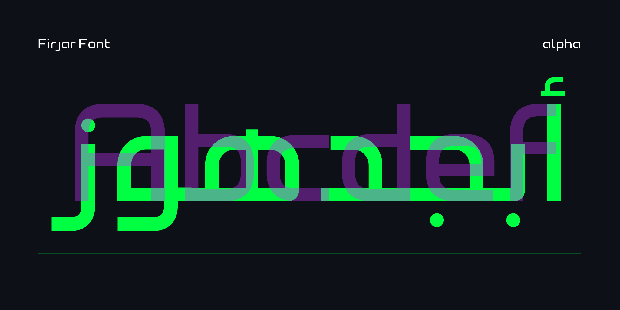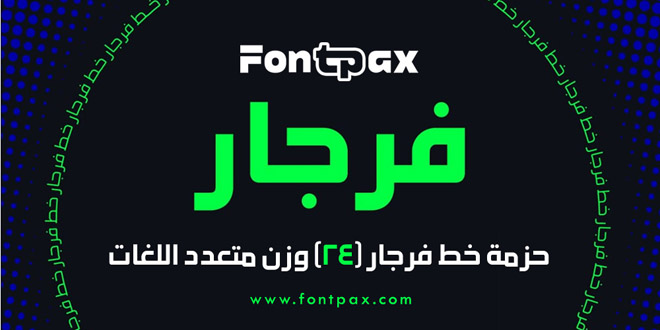
حزمة خط فرجار (24) وزن متعدد اللغات .. ملف يحتوي على حزمة خطوط فرجار عربي وإنجليزي وبأوزان مختلفة يصلح لكافة أعمال الكتابة للعناوين والنصوص، وهو متاح للتحميل المجاني الان.